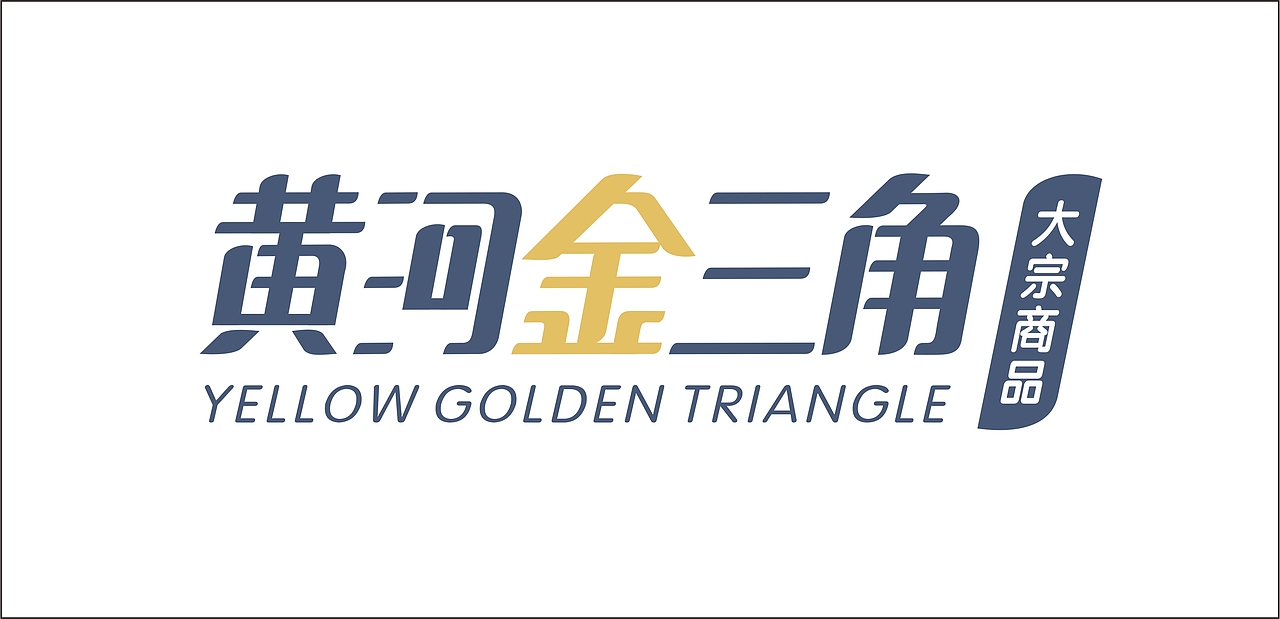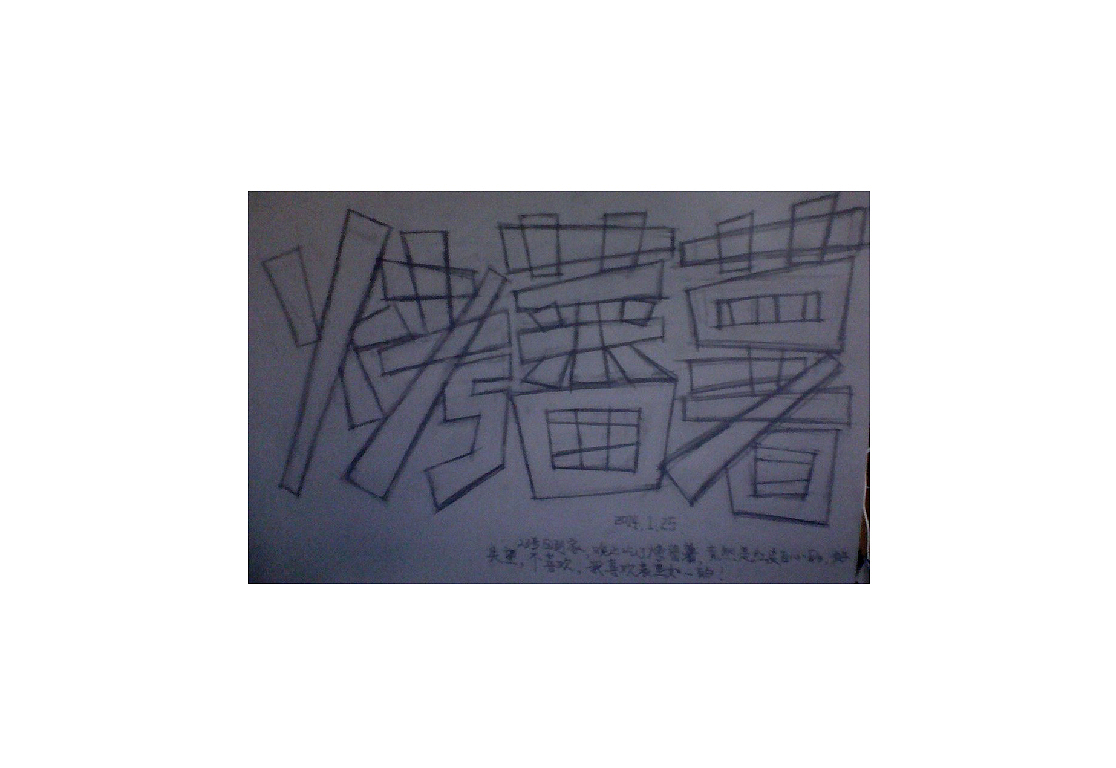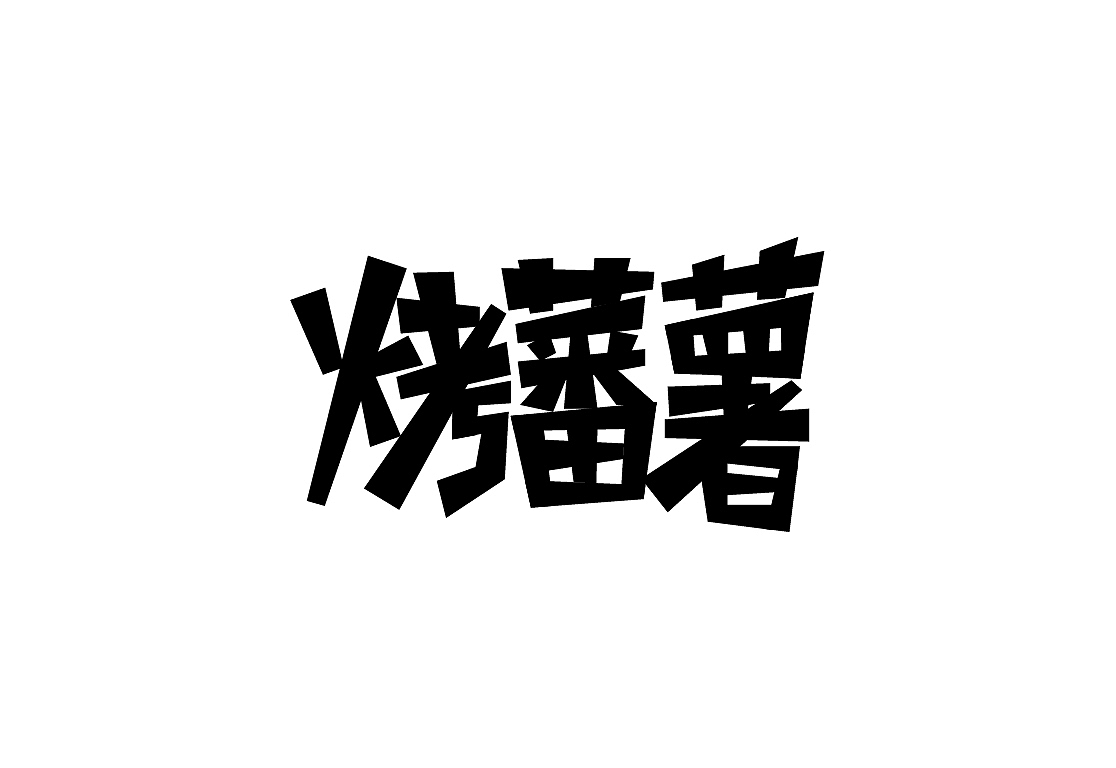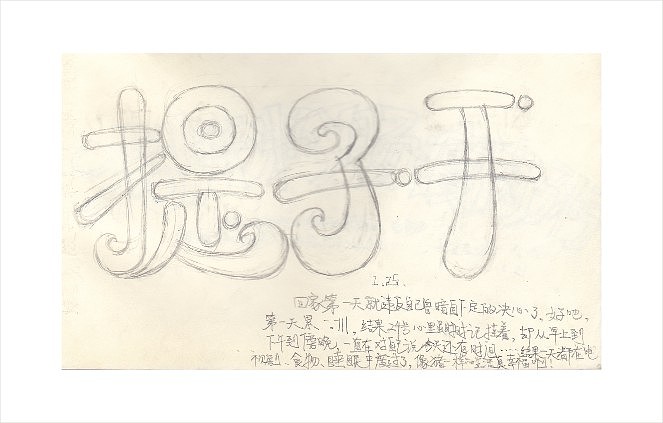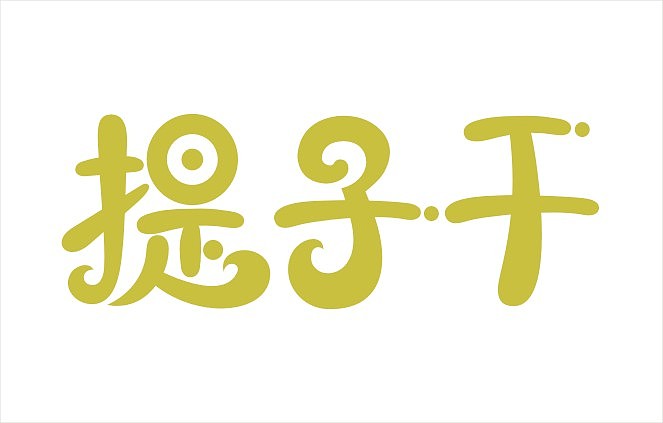
手绘字体设计,长期更新中……
这是去年的果脯果干包装上的字体设计,这其实是第二个方案,第一个懒得找了- 。-|||,设计得比较没特点
这是第三个方案,包装为同事所作,后来把字体发给了他,不知道有没有再变动呢
这是今年找工作时,其中一家公司出的一道,算是考题吧,有群友说很俗,囧~结果我也没到那间公司上班,选择永远是互相、相向的!
好久不更新了,看看手绘的日期还是1.25的,如今都7.23了,半年都已经过去了- 。-|||,各种懒各种忙各种借口……
2、描
3、调整
1.25……-。-|||